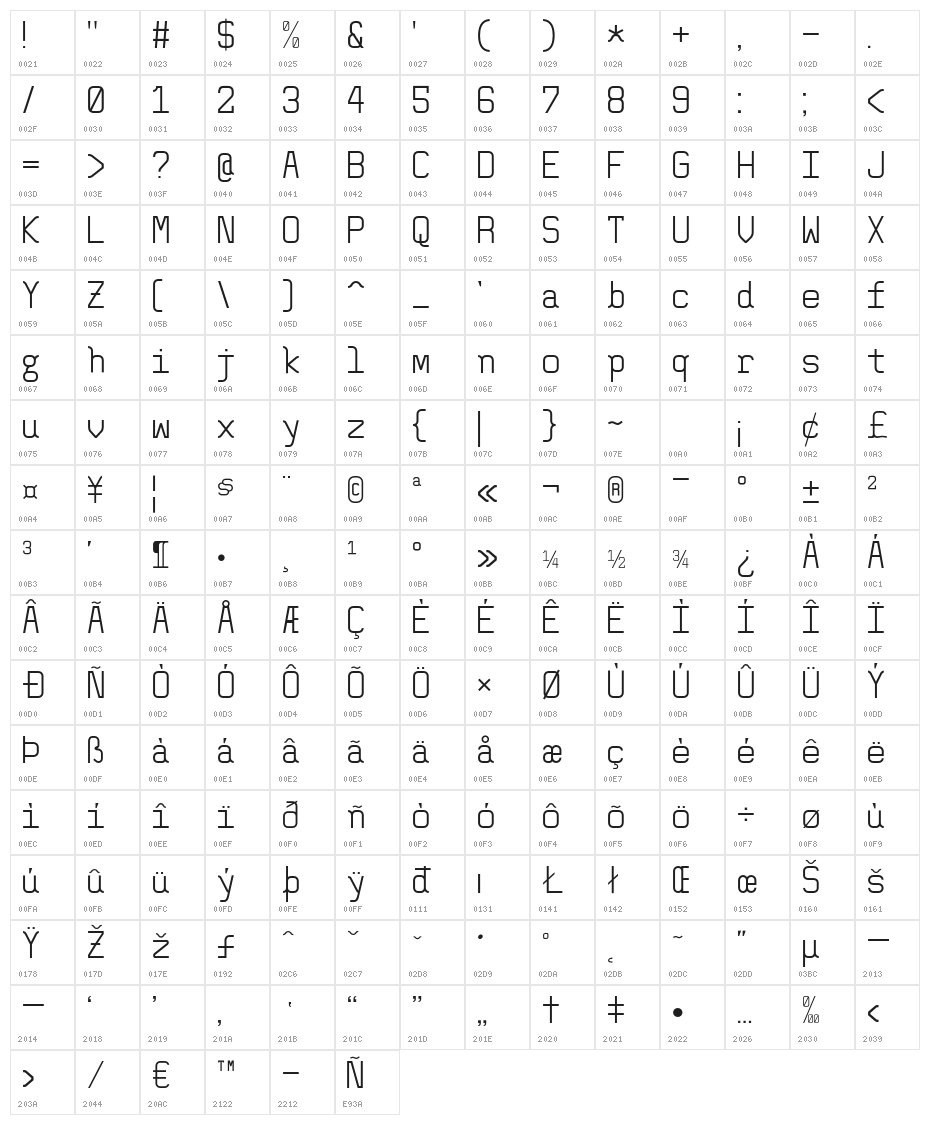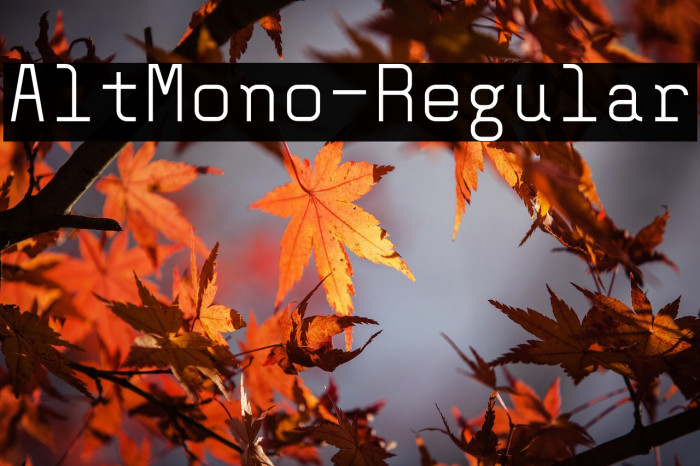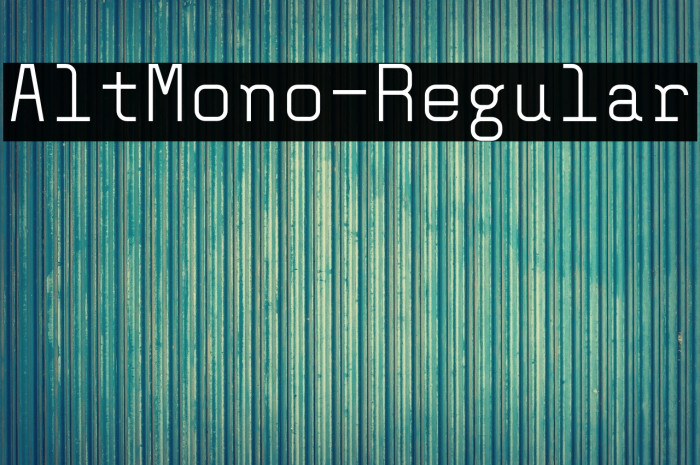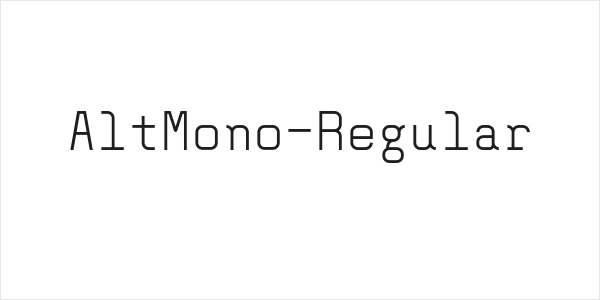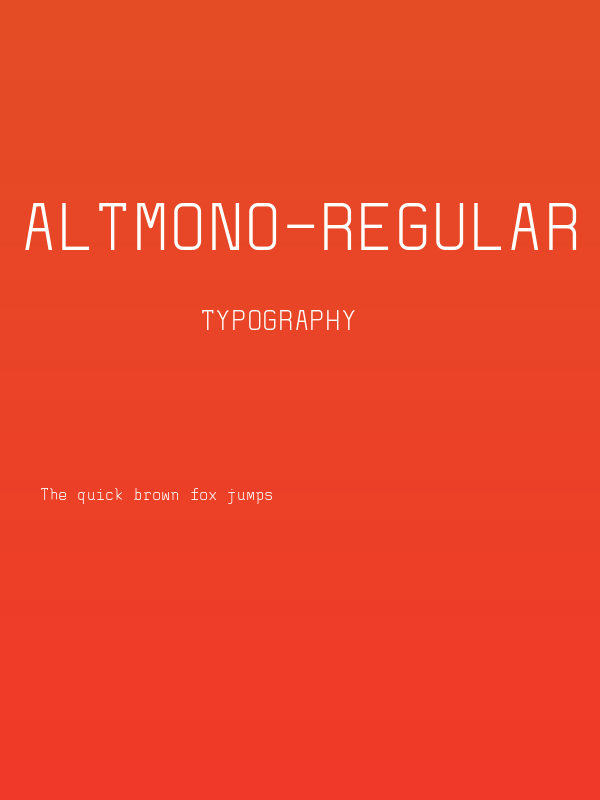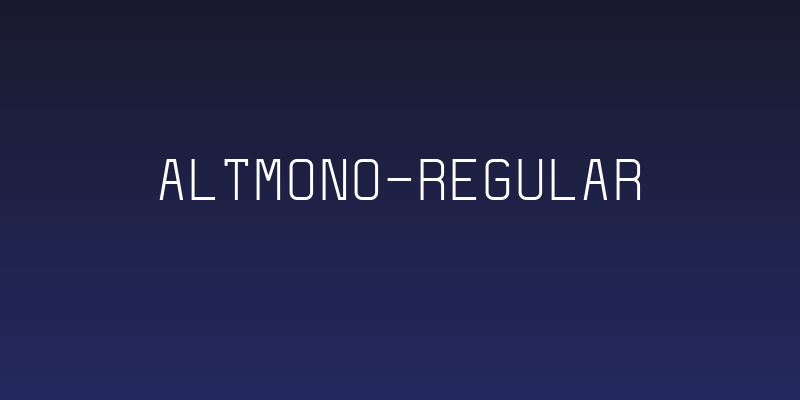
AltMono-Regular Font
| Caso d'uso | Coding, Technical documents, Data tables |
| Progetti proposti | Ideal for coding, technical documentation, data tables, and any project requiring a clear, uniform typeface. |